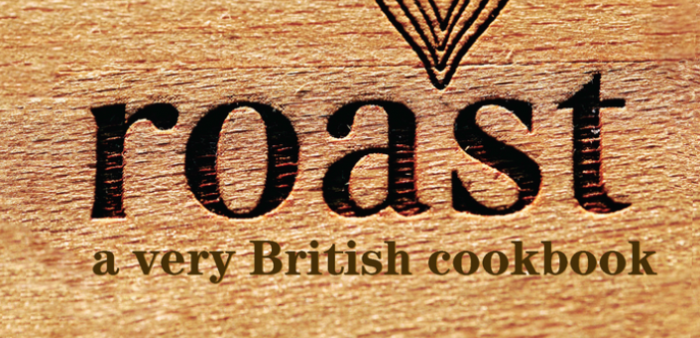
Ich bin auf der Suche nach der Font des Roast Kochbuchs. Hoffe ihr könnt mir helfen.
Das roast scheint in die Breite gezogen zu sein, die Breite im Logo sieht mir originaler aus:
Von der Grundform her würde die Avia passen, ich find aber auf die Schnelle keine, die der gesuchten wirklich entspricht. Vielleicht hat FontBureau ja eine "verbundene" Avia im Portfolio.